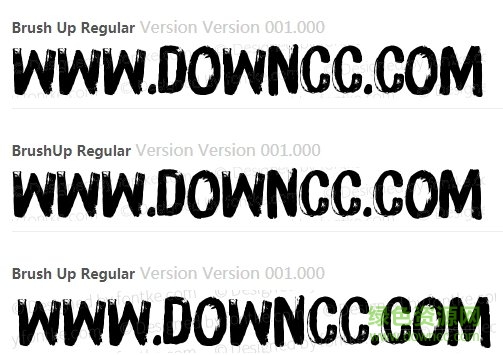
brushup ttf字體是一款有著潑墨風(fēng)格的毛筆書法字體,字跡明暗相間,很有水墨中國(guó)風(fēng)的底蘊(yùn),結(jié)構(gòu)上不拘一格,給人手寫字體的恣意體驗(yàn),喜歡這種風(fēng)格的可以來綠色資源網(wǎng)試試哦!
brushup字體字體包括Brush Up、BrushUp Regular兩個(gè)字重,無小寫表達(dá)方式,給文字更加清新大氣的視覺呈現(xiàn)。
brush up字體來自巴西設(shè)計(jì)公司Pintassilgo Prints,是一款擁有個(gè)性特色的常規(guī)字體,浪漫風(fēng)格國(guó)風(fēng)韻味,讓你的藝術(shù)設(shè)計(jì)、廣告策劃、ppt制作等更加與眾不同!